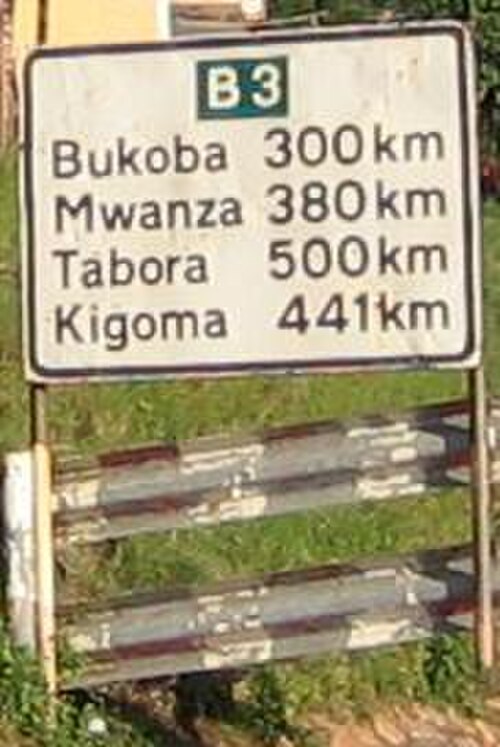
Transportは、イギリスの道路標識用に最初にデザインされたサンセリフ書体です。1957年から1963年にかけて、運輸省のアンダーソン委員会とウォーボーイズ委員会のデザイナーとして働いていたジョック・キニアとマーガレット・カルバートによって作成されました。[ 1 ] [ 2 ]
導入以前、イギリスの道路標識は、1933年のメイベリー報告書を受けて導入され、1955年から1957年にかけて改訂された、大文字のみのルウェリン・スミス体を使用していた。それ以前の標識は、フィンガーポストと呼ばれ、製造元から提供された様々なサンセリフ体を使用していた。これらの体のいずれかが使用されるような道路では、視認性はそれほど重要な問題ではなかったが、1950年代にイギリス初の高速道路が計画・建設されたことが、変化のきっかけとなった。
運輸省は1957年にコリン・アンダーソン卿を委員長とする高速道路の交通標識に関する諮問委員会を設置し、ジョック・キニアと彼の助手マーガレット・カルバートがグラフィックデザイナーとして任命された。標識のあらゆる側面が調査され、最初はプレストン・バイパス(1958年、現在はM6高速道路の一部)でテストされ、その1年後に(ロンドン-ヨークシャー)M1高速道路に導入された。委員会は他のヨーロッパ諸国やアメリカ合衆国の例も検討したが、キニアとカルバートはそれらをやや粗雑で不十分だと感じた。そこで彼らは、「a」「t」「l」に特徴的な尾部があり、分数に横棒のない、より丸みを帯びた書体を開発した。これらはすべて読みやすさの向上に役立った。
同省は、この取り組みの初期段階での成功を受けて、ウォルター・ウォーボーイズ卿を委員長とし、再びキニアとカルバートを設計者として起用した別の委員会を設置し、多目的道路の交通標識について検討させた。この取り組みの結果、1949年の国連道路・自動車輸送世界会議で推奨されたものに基づいたピクトグラム標識が導入された。
この書体には Transport Medium と Transport Heavy の 2 つの形式があります。どちらも基本的な形状は同じですが、Transport Heavy は太字で、非主要道路で使用されるような白地に黒文字の読みやすさを向上させます。一方、Transport Medium はより細字で、緑色の主要道路標識のように暗い背景に白文字で使用されます。[ 3 ]
英国の道路標識で使用できるフォントはTransportフォントのみです(高速道路標識は例外で、ルート番号はMotorwayと呼ばれる独自の書体で表示されます)。[ 4 ]:規則5およびスケジュール17
Transportフォントで使用できる記号は限られており、主にアポストロフィ、ポンド記号、½や⅓などの一般的な分数など、道路標識で一般的に使用される記号に限られています。オリジナルのTransportフォントには発音記号は含まれていませんでしたが、2016年の交通標識規則および一般指示の発行以降、スコットランドの道路標識で使用するためのグレイブアクセントが追加されました。[ 4 ]:スケジュール17
この書体は英国の道路標識用に開発されたものですが、英国政府のウェブサイトや一部の政府文書にも使用されています。また、世界中の多くの国々の道路標識にも使用されており、王室属領、英国海外領土、英連邦諸国における限定的な残存使用に加え、香港、アイスランド、アイルランド、ギリシャ(高速道路以外の道路)、ポルトガル、そして中東の多くの地域でも使用されています。これらの地域では、英語では使用されない発音記号やその他の文字を含めるための修正が加えられている場合も少なくありません。
インドネシアでは、電子可変メッセージ標識が2014年4月から運輸で使用されている。[ 6 ]
オリジナルのトランスポートファミリーは、2つの重量でURW++によってデジタル化されています。[ 7 ]
これは、A2/SW/HK Limitedのヘンリック・クベルとマーガレット・カルバートによって2012年に開発された、オリジナルの書体のアップデートおよび拡張版です。
オリジナル版には、補完的な斜体スタイルを備えた 6 種類のウェイト (Thin、Light、Regular、Medium、Bold、Black) が含まれています。また、テキスト数字やスモールキャピタルなどの他の機能も備えています。[ 8 ] Semibold ウェイトは、2018 年 8 月 2 日[ 9 ]から 2018 年 9 月 2 日[ 10 ]の間に追加されました。
これは、New Transport のデザイナーによってデザインされた New Transport のカスタム バージョンで、2012 年に英国政府デジタル サービス Web サイト ( GOV.UK ) で使用するために作成され、すべてのテキストの唯一のフォントとして選ばれました。[ 11 ] [ 12 ]
Transportをベースにした、アップデートされた非公式のファミリーが、2008年に独立系フォントメーカーのK-Typeによって初めてリリースされました。このファミリーには、Light、Medium、Heavyのウェイトに加え、2015年に追加された真のイタリック体が含まれています。[ 13 ]
Jörg Hemker は Transport 書体からインスピレーションを得た FF Nort と FF Nort Headline という 2 つの書体をデザインしました。どちらの書体もギリシャ文字とキリル文字をサポートしています。[ 14 ] [ 15 ]